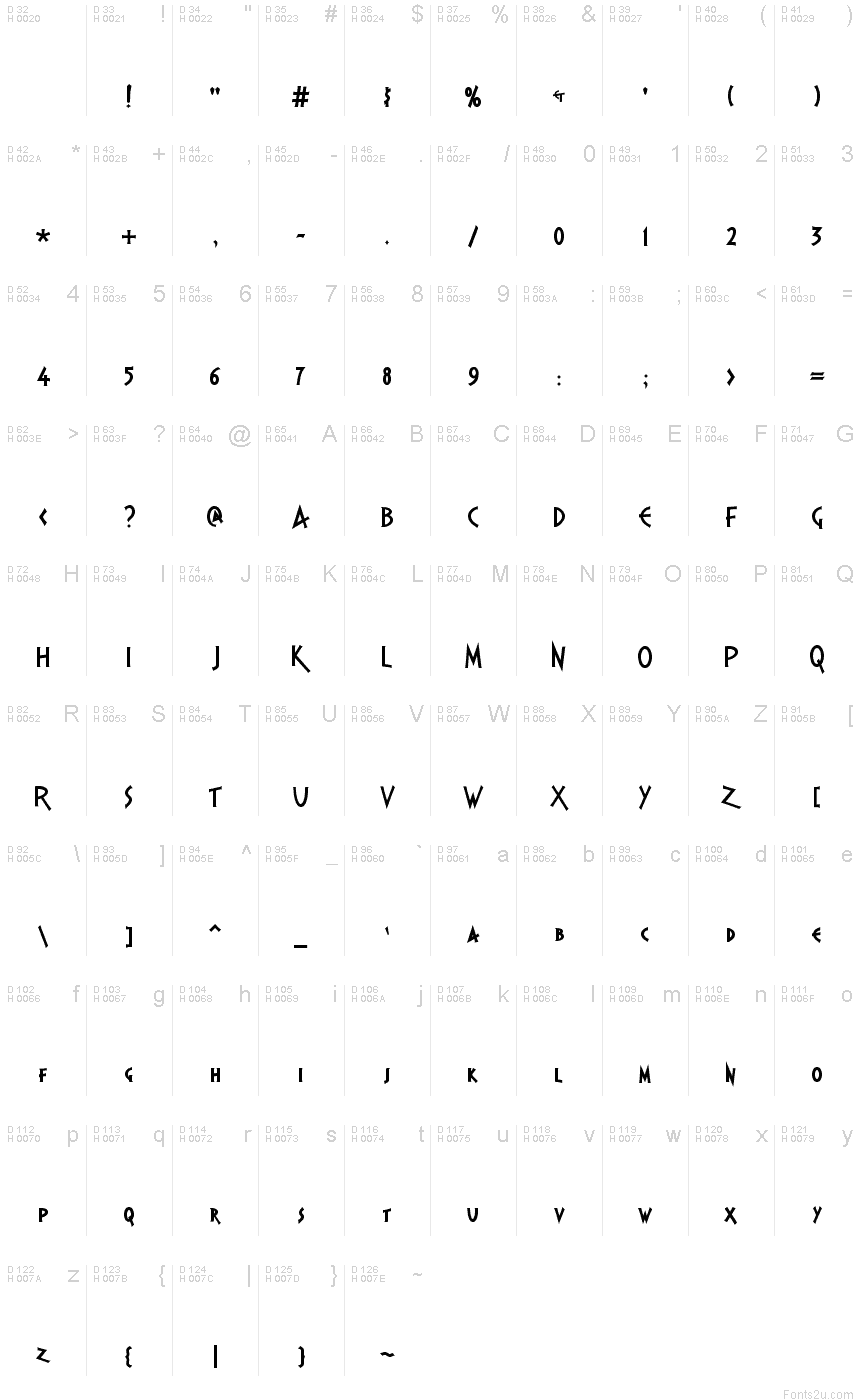
PR Agamemnon  Bold, Top Lining
PR Agamemnon di Peter Rempel è un font display gotico moderno e gratuito dal ritmo irregolare e teatrale. Le lettere mescolano tratti spessi e scuri con punte affilate e tagli obliqui; il risultato è una forma che appare inquieta, con un tocco medievale piuttosto che solenne.
È una scelta naturale per copertine di libri fantasy, volantini metal, titoli di giochi, poster e per l'immagine coordinata di eventi a tema horror, dove questo font gratuito riesce a trasmettere rapidamente un tono drammatico e carico di atmosfera. Funziona bene anche per loghi brevi e monogrammi: grazie alle giunzioni inclinate e alle punte simili a lance, anche poche lettere acquisiscono una presenza emblematica e incisiva.
PR Agamemnon è un font che prende il nome dall'eroe greco Agamennone.
Maiuscole e minuscole usano lo stesso spessore di tratto, con un rapporto dimensionale di 5 a 8, simile alla cosiddetta "sezione aurea".
Il font include tutti i caratteri accentati per le lingue dell'Europa occidentale e un set completo di caratteri greci.